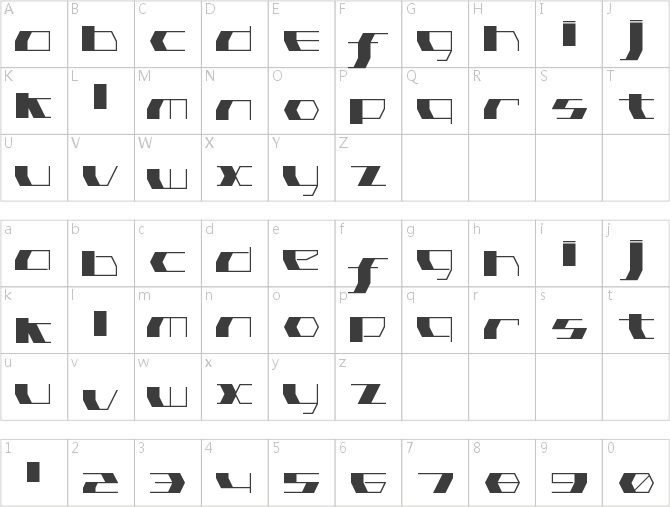
pink_has_gone_extinct_ultra_thin 詳情頁
pink_has_gone_extinct_ultra_thin
pink_has_gone_extinct_ultra_thin字體字庫是一款讓人賞心悅目、百看不厭的英文字體,適合各類廣告和產(chǎn)品包裝設計應用,字體大小0.01MB,格式為ttf字體,上傳用戶是文生電腦,作者/版權方為未知